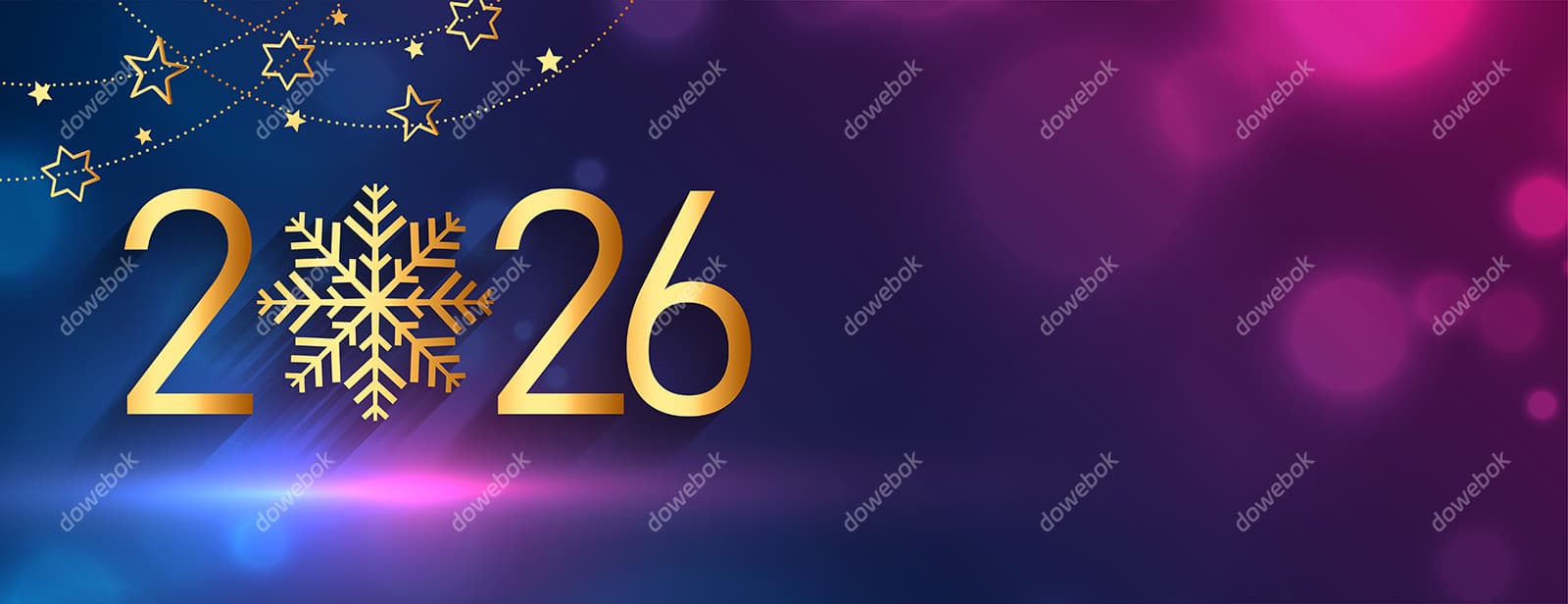
这是一款由金色雪花和数字设计的 2026 新年快乐 banner 矢量素材,紫蓝渐变背景晕染着光斑,营造出梦幻氛围。金色 “2026” 字体间嵌着精致的金雪花装饰,左上角悬着串线金星,整体色调华丽且清透。雪花与星光元素呼应冬日氛围,金与渐变紫蓝的搭配既显新年的喜庆,又传递出浪漫的节日质感,适配冬季新年贺卡、电子祝福等场景。